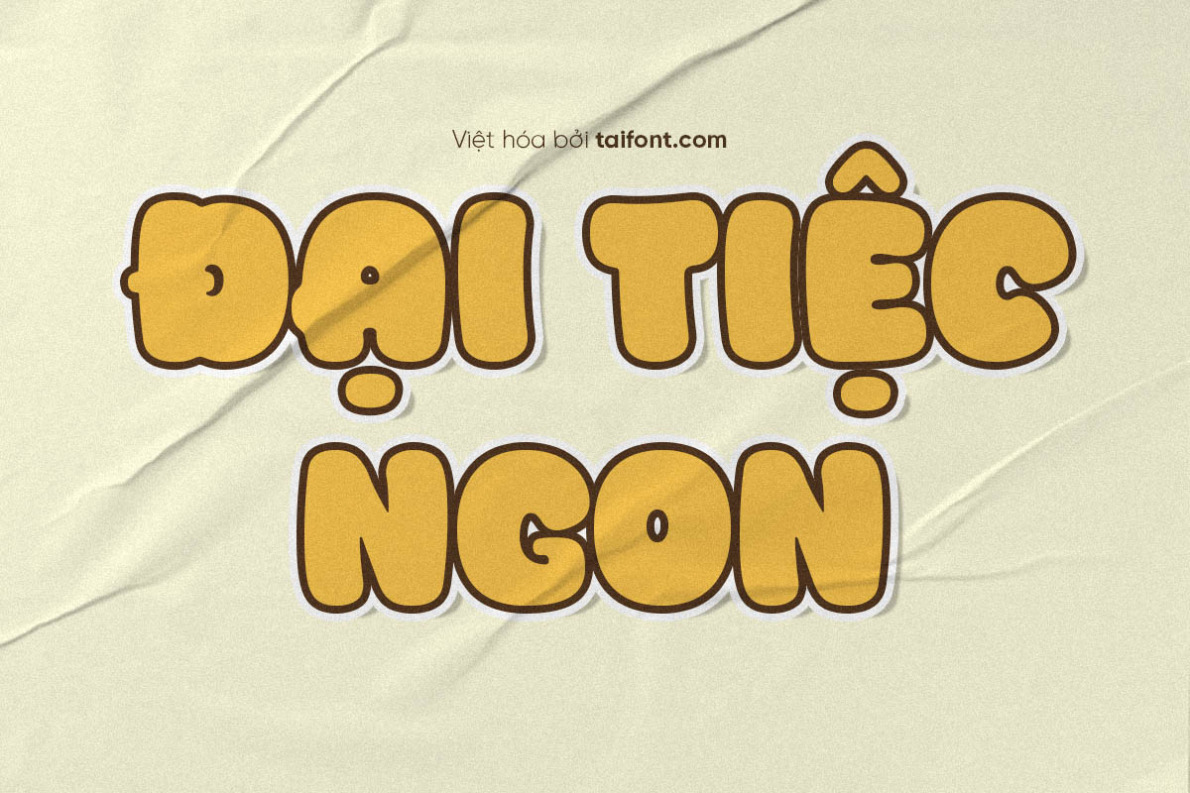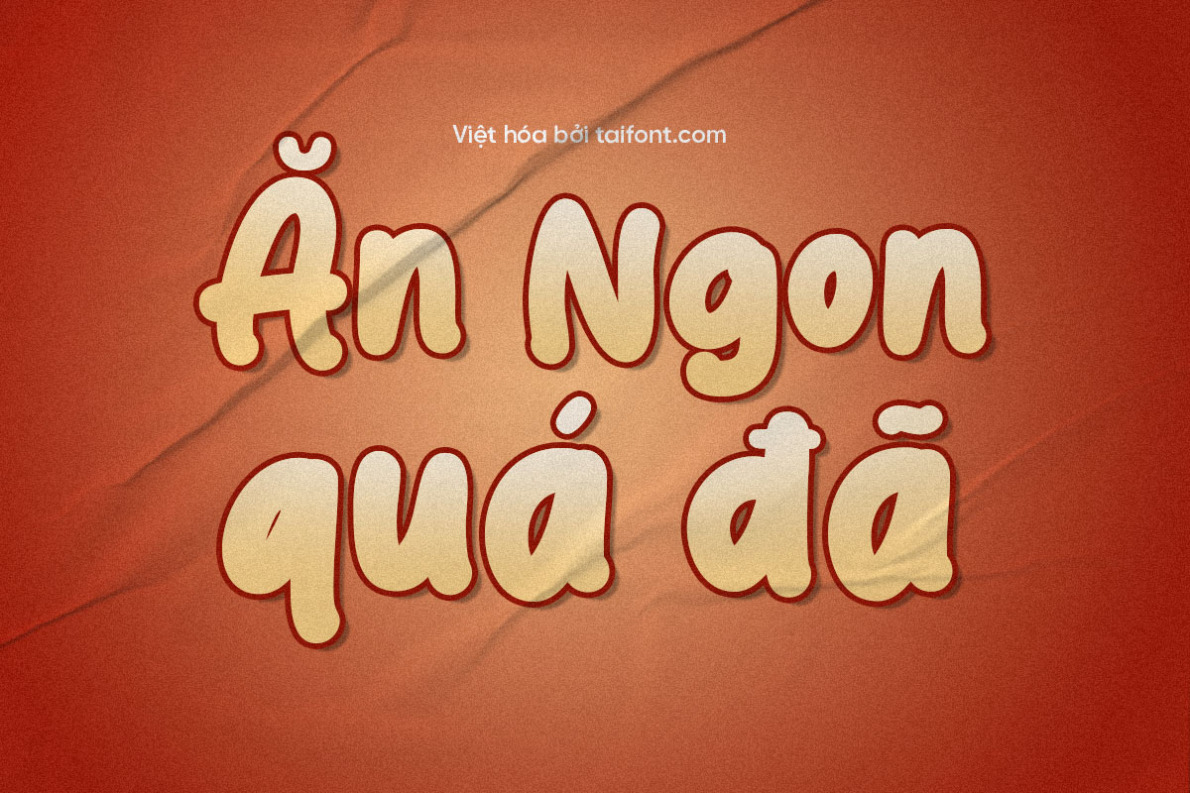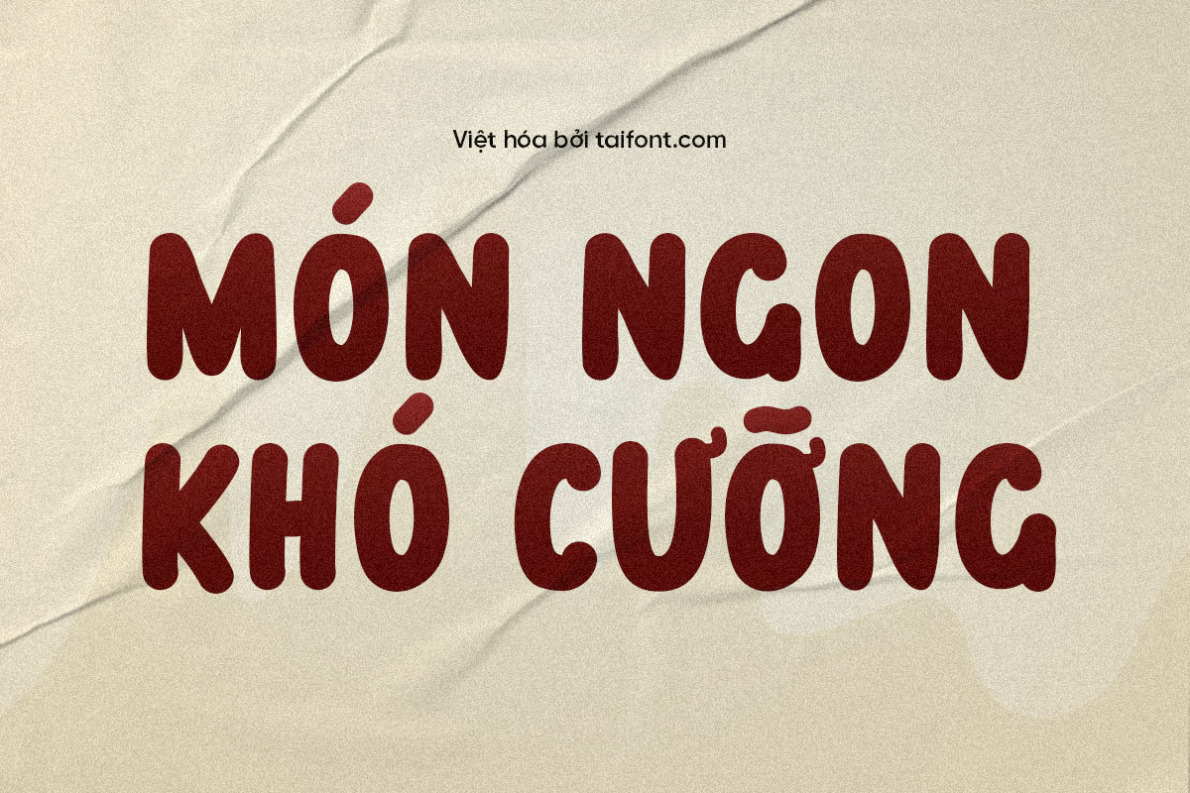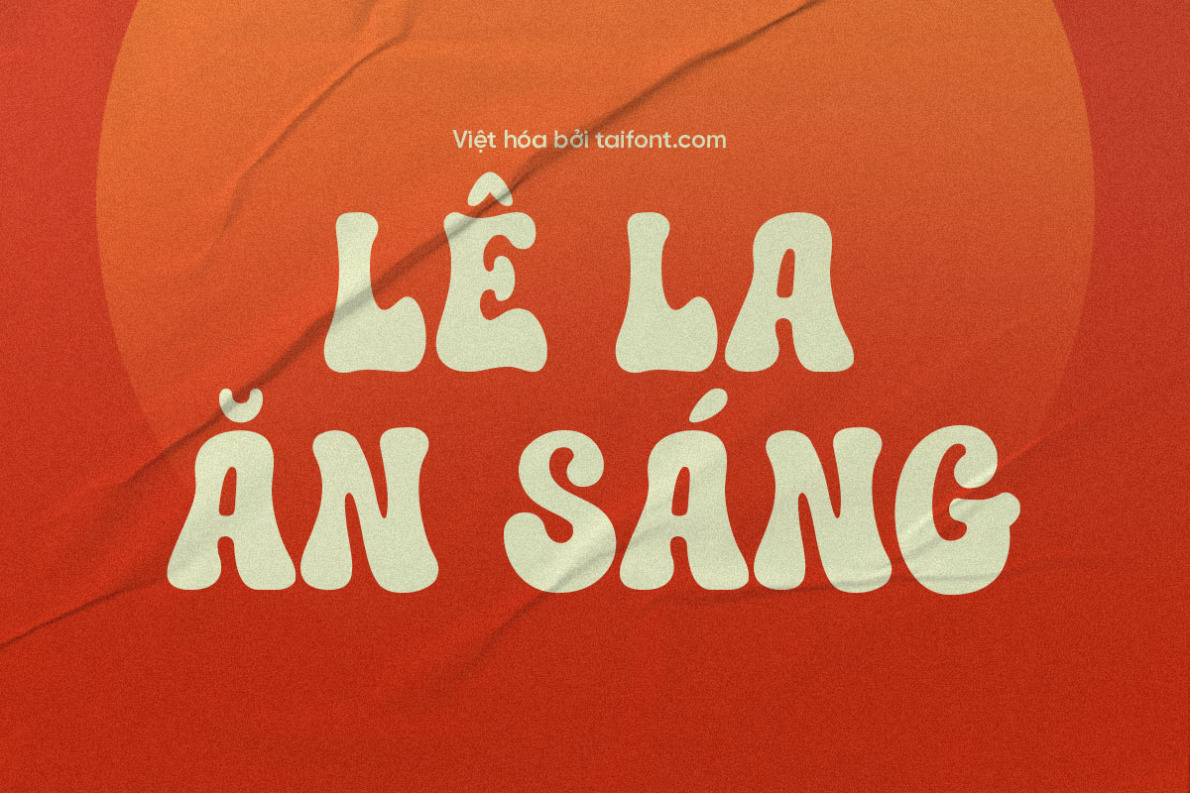
Top 5 Font Việt Hóa Chủ Đề Ẩm Thực Đẹp Mắt Cho Thiết Kế Menu, Áo Thun, Bao Bì
Font Việt Hóa Chủ Đề Ẩm Thực – Sự Lựa Chọn Tuyệt Vời Cho Thiết Kế Sáng Tạo
Thiết kế trong lĩnh vực ẩm thực đòi hỏi sự hấp dẫn, ngọt ngào và đôi khi đầy vui nhộn. Một font chữ phù hợp có thể “nêm nếm” thêm hương vị cho sản phẩm của bạn. Dưới đây là 5 font Việt hóa chủ đề ẩm thực đẹp mắt, dễ dùng, hoàn hảo cho các dự án thiết kế menu, bao bì, áo thun, poster món ăn, hoặc các thương hiệu liên quan đến thực phẩm.
1. TF Atop – Font script nhẹ nhàng, đậm chất handmade
TF Atop mang phong cách viết tay bay bổng, rất hợp với các thiết kế món ăn homemade, tiệm bánh nhỏ, hoặc thương hiệu thiên về cảm xúc. Font có độ cong nhẹ và dễ đọc, thích hợp làm tiêu đề chính hoặc chữ trang trí.
2. TF Bubble Candy – Font tròn trịa vui nhộn như kẹo ngọt
Đúng như tên gọi, Bubble Candy là font chữ tròn trịa và vui vẻ như viên kẹo. Đây là lựa chọn hoàn hảo cho các thiết kế bao bì snack, quán ăn vặt, hay thực đơn cho trẻ em.
3. TF Canyon Bright – Font trang trí độc đáo cho áo thun ẩm thực
Canyon Bright có cá tính mạnh, với nét chữ bo góc độc đáo. Dễ dàng sử dụng cho các mẫu thiết kế áo thun chủ đề đồ ăn, quán ăn đường phố, hay các poster món ngon truyền thống.
4. TF Guava Harvest – Font đậm cho ẩm thực
Guava Harvest đem lại cảm giác nhiệt đới tươi mát với kiểu chữ dày, dễ nhìn. Font rất phù hợp với thương hiệu nước trái cây, siêu thị trái cây, hoặc các nội dung quảng bá về sản phẩm nông nghiệp sạch.
5. TF Mother’s Holiday – Font đầy thú vị
Font mang đến cảm xúc dịu dàng, ấm cúng – lý tưởng cho những thiết kế menu món gia đình, các dịp lễ, hoặc sản phẩm liên quan đến món ăn truyền thống.
Kết luận
Nếu bạn đang làm thiết kế cho lĩnh vực thực phẩm, hãy chọn font phù hợp với tinh thần món ăn và đối tượng khách hàng. Bộ 5 font Việt hóa trên là khởi đầu lý tưởng cho những ai yêu thích sự sáng tạo trong thiết kế ẩm thực.